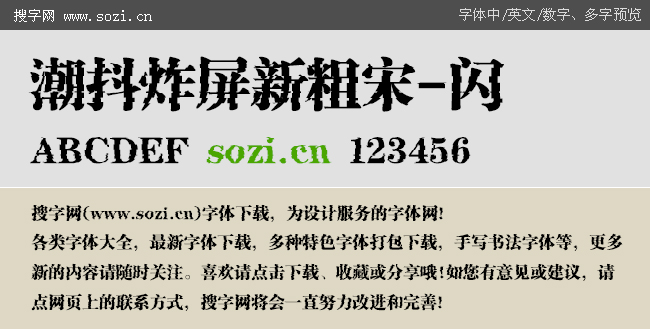
潮抖炸屏新粗宋-閃
搜字網(wǎng)提供一款潮抖炸屏新粗宋-閃中文字體下載,潮抖炸屏新粗宋-閃是一款藝術(shù)粗宋字體,潮抖炸屏新粗宋以粗宋字為基準(zhǔn),加入抖動(dòng)筆畫(huà)與切割錯(cuò)位效果,潮流動(dòng)感,重新定義時(shí)尚字體。適合用于標(biāo)題設(shè)計(jì)、海報(bào)設(shè)計(jì)、包裝設(shè)計(jì)等場(chǎng)景廣泛應(yīng)用。(本字體為個(gè)人非商用版,商用請(qǐng)聯(lián)系作者購(gòu)買(mǎi)授權(quán)。官方網(wǎng)址:http://www.reeji.com 聯(lián)系方式:021-58597892)